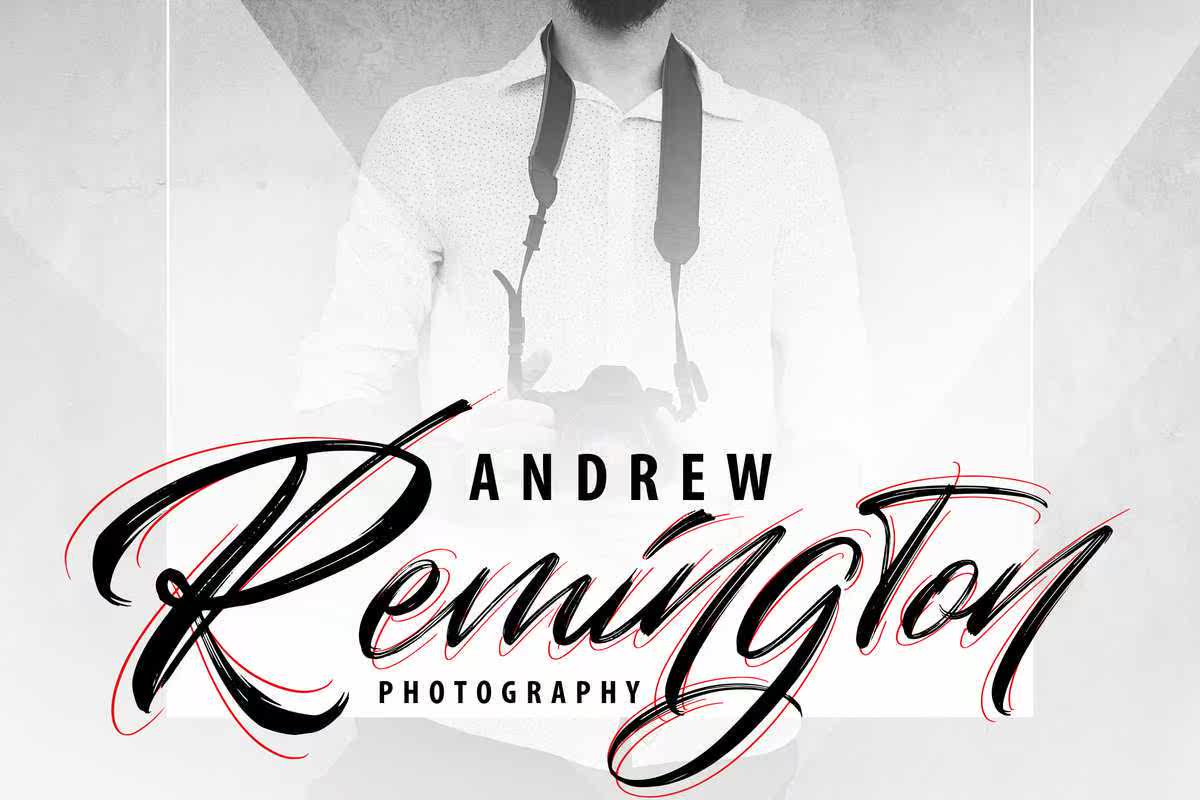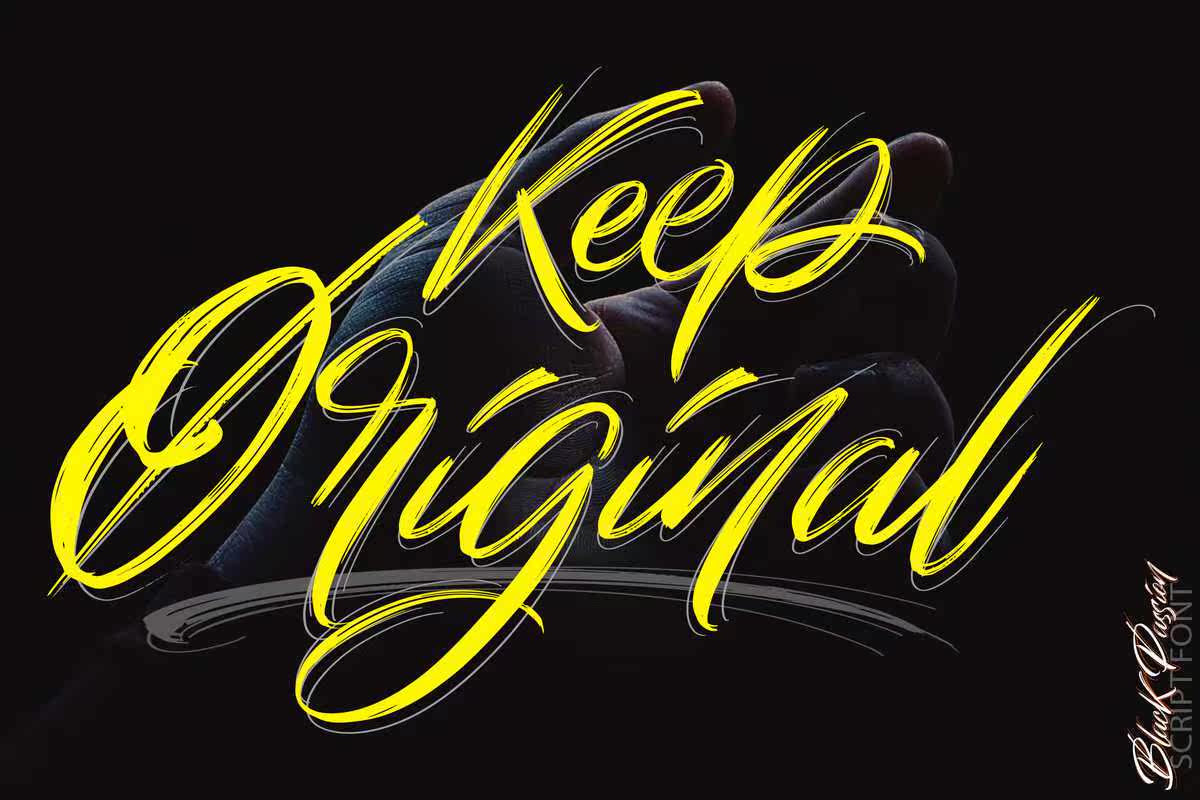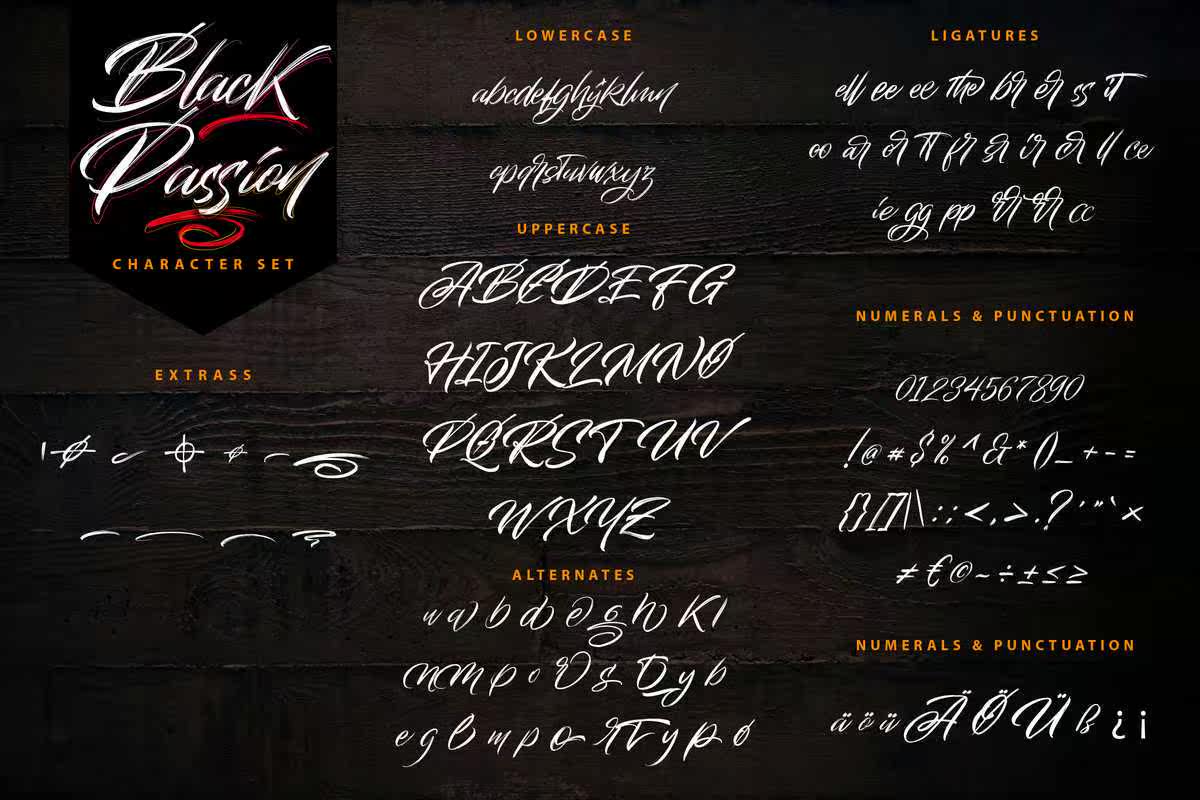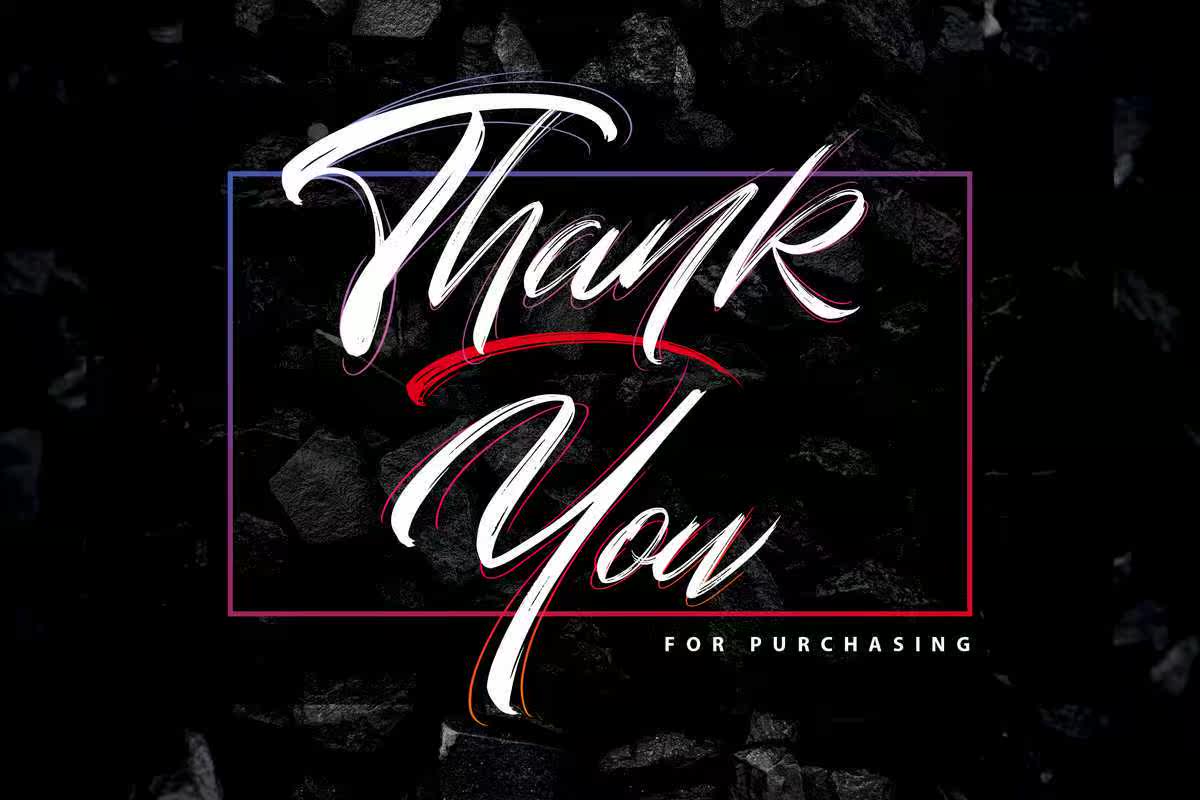
黑色激情是一种精致的手工画笔脚本类型,可利用其独特的方式制作出一种全面的字体。它的内容可能看起来对眼睛不太合适,但却体现出丰富的内涵和独特性。感谢手工制作的字体外观——黑色激情完美无瑕地满足了你的欲望,并可用于创作你喜欢的语录、创作你的音乐,写杂志,还有更多。黑色激情是手工制作的毛笔脚本式字体,利用它可以制作出一个全面的字体。这些内容可能看起来对你来说不重要,但却有着丰富的内涵和独特性。感谢手工制作的字体——黑色激情是完美的,满足了你的欲望,并且可以很好地用于创作你喜欢的语录、写音乐、写杂志等等。